Rollen oder Schlagen?
Ein Film dauert 90 Minuten, möchte ich in bewusstem Anklang an Fußball-Zitate sagen. Man nimmt sich eine gewisse Zeit dafür. Man lässt sich darauf ein, dass sich der Stoff entwickelt, man die handelnden Personen kennenlernt, auch mancher Umweg gegangen wird, der sich später vielleicht als zentral herausstellt. Und man konzentriert sich in gewisser Weise. Ablenkende Dinge drumherum werden reduziert. Auch wirklich niemand käme auf die Idee, dass irgendwo im Filmbild ständig eingeblendet würde, an welcher Position (Fortschrittsbalken) oder Filmminute man sich befindet. Das wäre dem Filmgenuss abträglich.
Und an dieser Stelle möchte ich den Blick schwenken auf ein anderes Medium: Das Buch. Genauer noch: Das Buch der Bücher.
Inhaltlich stecken im Text dieses Buches viele Filme, spannende und langweilige: Erzählungen, Dokumentationen, Dramen, Parabeln und Gleichnisse, langweilige Historien und Listen, Gesetzestexte ebenso wie aufrüttelnde Katastrophen, Entwicklungs- und Charakterstudien, Sprichwörter und Visionen.
Ich liebe Bücher. Soviel vorweg. Sehr sogar. Aber mir kommen Zweifel, ob das Prinzip des Buches nicht manchmal seinem Inhalt in die Quere kommen kann. Bücher schlagen wir auf - an beliebiger Stelle. Sprache ist manchmal verräterisch: Schlagen? Hier setzt mein Zweifel ein.
Denn was ich in vielen Bibelausgaben der letzten 30 Jahre sehe, ist das Aufschlagen auf die Spitze getrieben:
Dicke Überschriften portionieren mir den Text - ein bisschen wie Chicken McNuggets. Große und fette Zahlen machen es mir möglich, schnell direkt zur angesteuerten Stelle zu finden. Und möglicherweise sind die Verse mit Ziffer sowieso gleich jeweils als eigener Absatz gesetzt. Ein Nachschlagewerk - aber nichts zum Lesen. (Bild 1, 2)
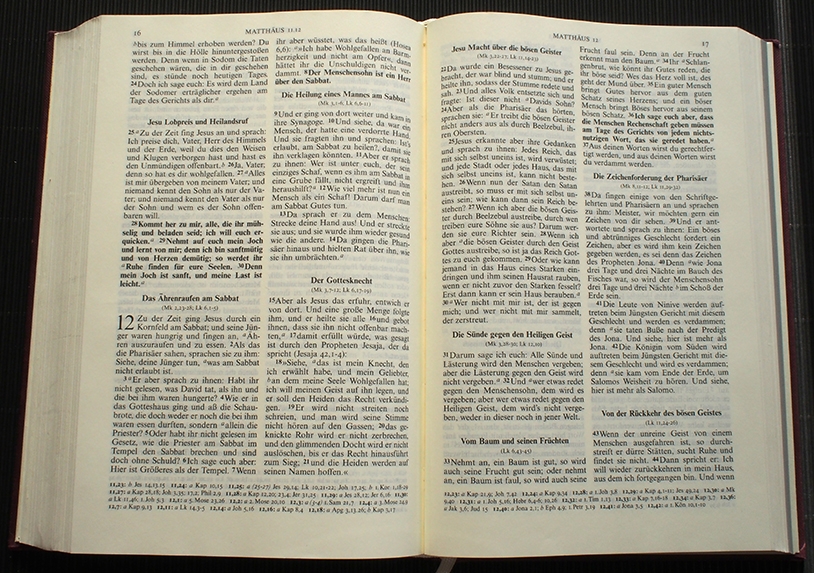
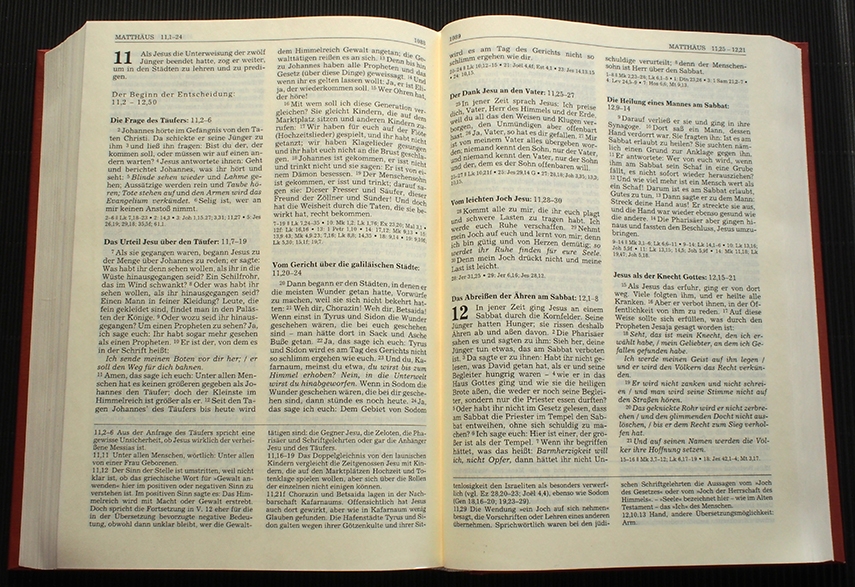
Praktisch. Aber Geschichte, Erzählbogen, Spannung oder Überraschung will sich so nicht mehr einstellen. Wir haben es hier mit maximierter referenzierender bzw. konsultierender Leseart zu tun. Aber wer braucht das? Es ist ein Vorzug, Jugendliche dabei erleben zu dürfen, wie sie mit so etwas umgehen. Wenn man ihnen (notabene: ich verallgemeinere freilich unzulässig, ausschließlich um zu pointieren) sagt »Schlage mal Mt 6,33 nach«, dann tun sie genau das und lesen eine steile und vermutlich fett hervorgehobene Aufforderung. Den Text davor lesen sie möglicherweise nicht. Und bekommen so eine falsche Vorstellung. Wer so »Casablanca« anschauen würde, hätte den schlechtesten Eindruck und nichts vom Film. Mal ganz abgesehen davon, dass Papier, Schriftgröße und Schriftart, Proportionen usw. in vielen so günstig ausgegebenen Bibelausgaben auch nur zum Nachschlagen und nicht zum Festlesen also linearer Leseart einladen. (Bild 3)
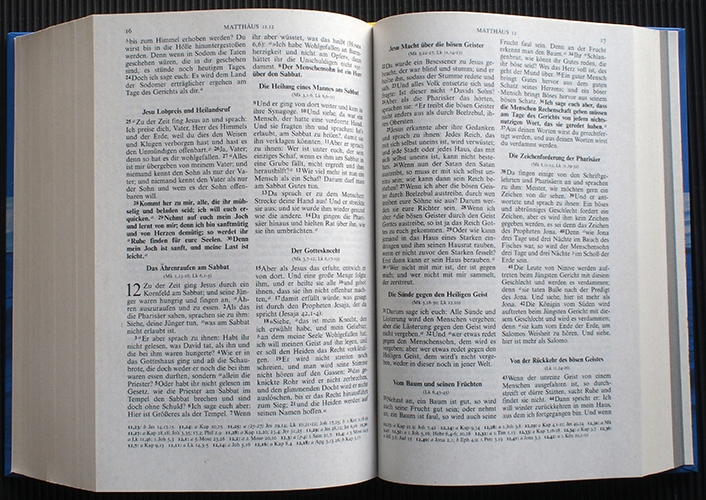
Man muss dazu wissen, dass in ihrem Ursprung die Bibelinhalte doch ganz anders überliefert waren. Nämlich in aller Regel mündlich. Erzählt. Von Menschen, die sicher nicht aufgefordert wurden »sag doch nochmal den 25. Satz deines dritten Abschnitts«. Aufgeschrieben wurden diese Inhalte dann zuerst ohne Punkt und Komma (teils sogar ohne Leerzeichen) und auf Rollen. Also so, dass sie als ein Zusammenhang in die Hand und vors Auge kamen. (Bild 4, 5)
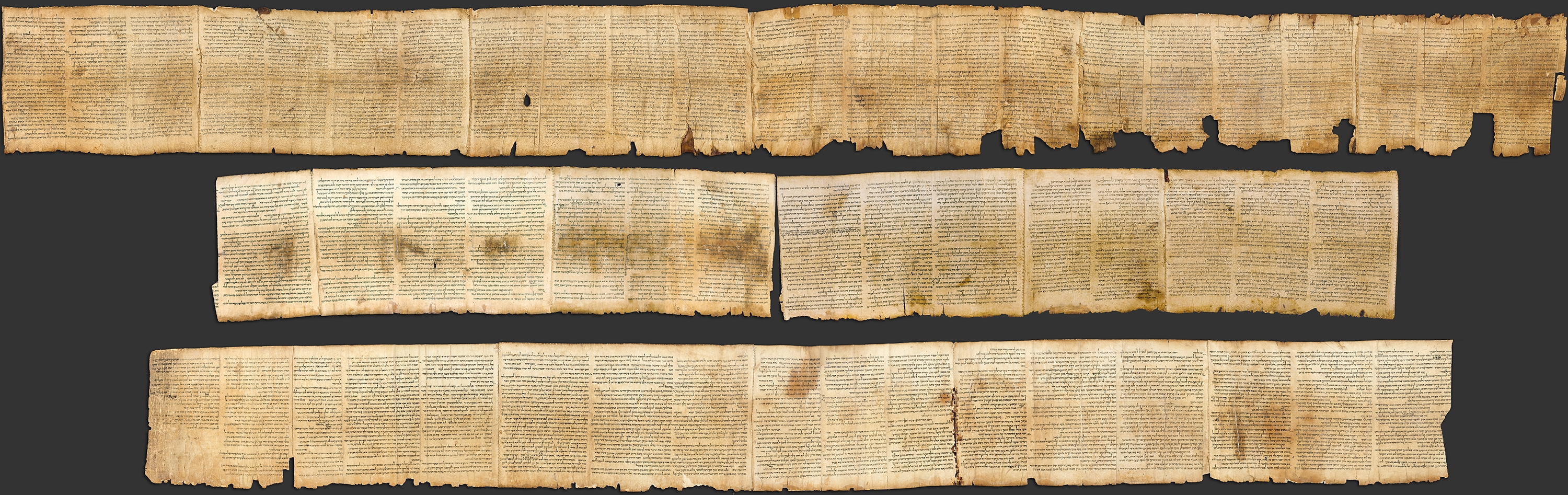
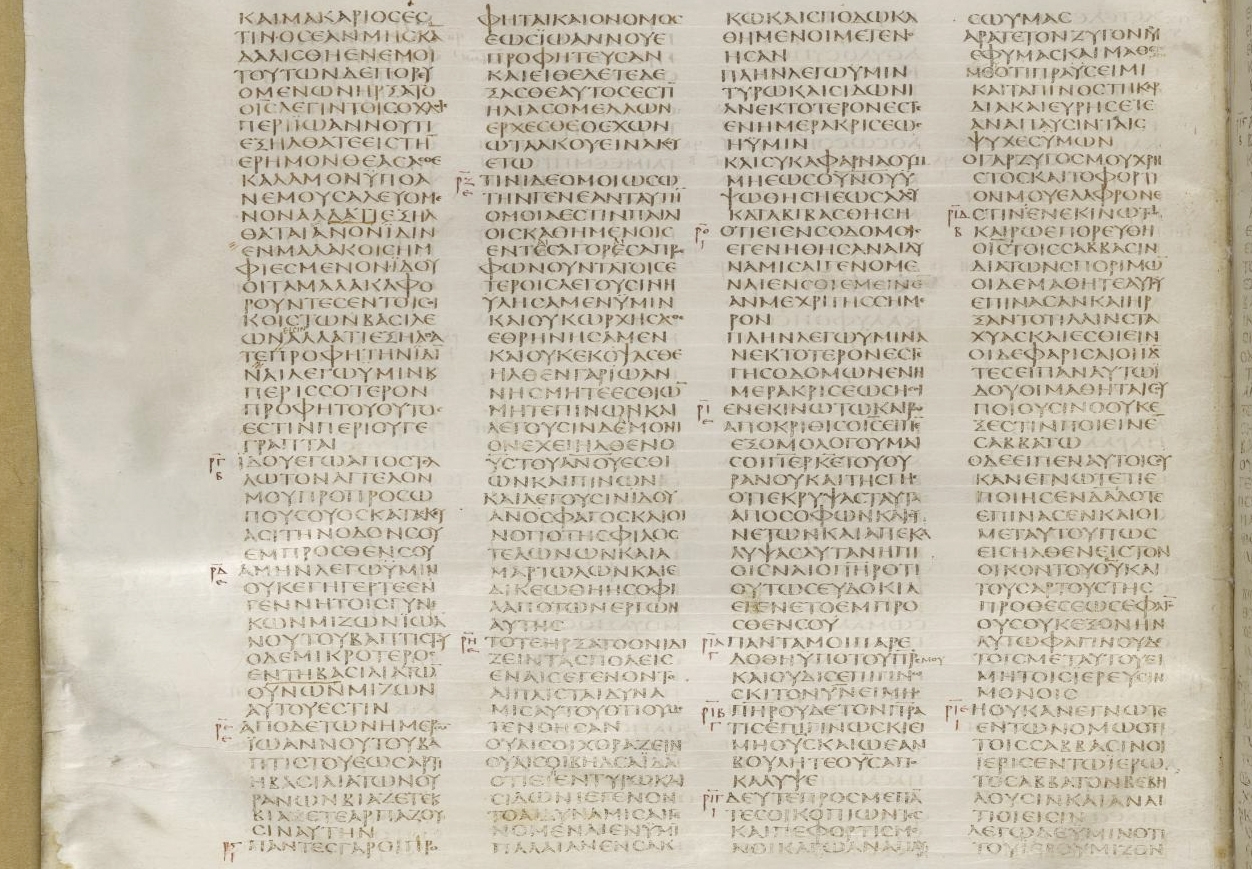
Die Kapiteleinteilung erfolgte erst ab dem 4., endgültig erst im 13. Jahrhundert nach Christus, die weitere Unterteilung in Verse sogar erst im 16. Jahrhundert, als erste wissenschaftliche Ausgaben entstanden. (Bild 6) Die Überschriften in unseren Bibelausgaben sind gar nicht Bestandteil des eigentlichen Textes, sondern im Kern willkürliche Unterteilungen und Ergänzungen, auch wenn sie natürlich ihren Sinn haben. Aber sie geben immer auch eine bestimmte Deutung wieder. Es macht einen großen Unterschied, ob ein und derselbe Abschnitt Der verlorene Sohn oder Der liebende Vater überschrieben wird. Der haptische und als verschiedenes Wahrnehmen erfahrene Unterschied zwischen dem Auf-Rollen einer Schriftrolle und dem Auf-Schlagen eines Buches markiert für mich hier einen Horizont für typografische Entscheidungen: Rollen oder schlagen wir den Text?
Sicher, biblische Texte sind manchmal sperrig. Und sie sind fremd. Sie erschließen sich manchmal erst nach einiger Zeit. Aber das tut »Casablanca« auch. Dem Film geben wir die Zeit. Warum dem Text nicht?
Fremdheit muss man aushalten. Man muss sie stehen lassen, denn so bleibt auch das Eigene stehen. Im Sich-damit-auseinander-Setzen kann man sich dann auch gegenseitig die Ehre geben.
Wir machen uns aber die Texte verfügbar, wenn wir sie in kleine Häppchen zerschneiden. Wir schlagen auf, statt zu entfalten. Es muss schnell gehen und direkt, ohne Zeit zu verlieren. Dabei verlieren wir aber auch uns selbst als Leser, der nachdenkt und sich auseinandersetzt. Häppchen werden gegeben und geschluckt. Ist es aber nicht erwachsener, sein Essen selbst zu zerlegen? Und befriedigender?
Allzu vor-zerlegte Texte verlieren den Kontext, er verschwindet aus dem Blickfeld. Die aufgeschlagenen Worte haben keine Rolle mehr und unsere Rolle dem Text gegenüber wird unklar. Schläger vielleicht? Aber ein geschlagener Text schlägt zurück. Bei der Bibel ist das so.
Die Schriftrolle oder ein fortlaufender Text erinnern dagegen immer daran, dass da noch mehr ist, und dass wir nur einen Teil sehen.
Der Leser muss sich dann seinen Ausschnitt selbst suchen, zurechtschneiden - aber er wird sich dabei viel mehr seiner eigenen Rolle bewusst, er ist eigentlich aktiver. Und er bemerkt viel eher die Fragmentarität des Gelesenen. Das ist gut. Beide, Leser und Text behalten ihre Ehre.
Der Leser darf suchen, darf sich fragen, wundern, zweifeln: »Ist das das letzte Wort dazu?« Aufrollen heißt auch entdecken, Nuancen feststellen, Zusammenhänge begreifen. So wie beim Wiederanschauen eines Films. Eigentlich schön, dass Filme in Rollen daherkamen und so klar ist: Man kann nicht so ohne weiteres einen Teil daraus entnehmen und verselbständigen, der Zusammenhang zählt.
Aber so radikal muss es ja nicht sein. Es reicht schon, wenn im Buch beim Aufschlagen der zusammenhängende Text im Vordergrund steht, gleichsam eine gedachte Rolle, wenn sofort klar ist: Über diesen Satz, diese Seite hinaus gibt es mehr, was ich jetzt sehe, ist nur ein Teil einer größeren Einheit. Und wenn die Zielmarken fürs Referenzieren nicht groß über den Text herrschen.
Wie gesagt: Ich liebe Bücher. Aber nicht das Schlagen. Die Bibel würde ich in Zukunft gerne aufblättern.